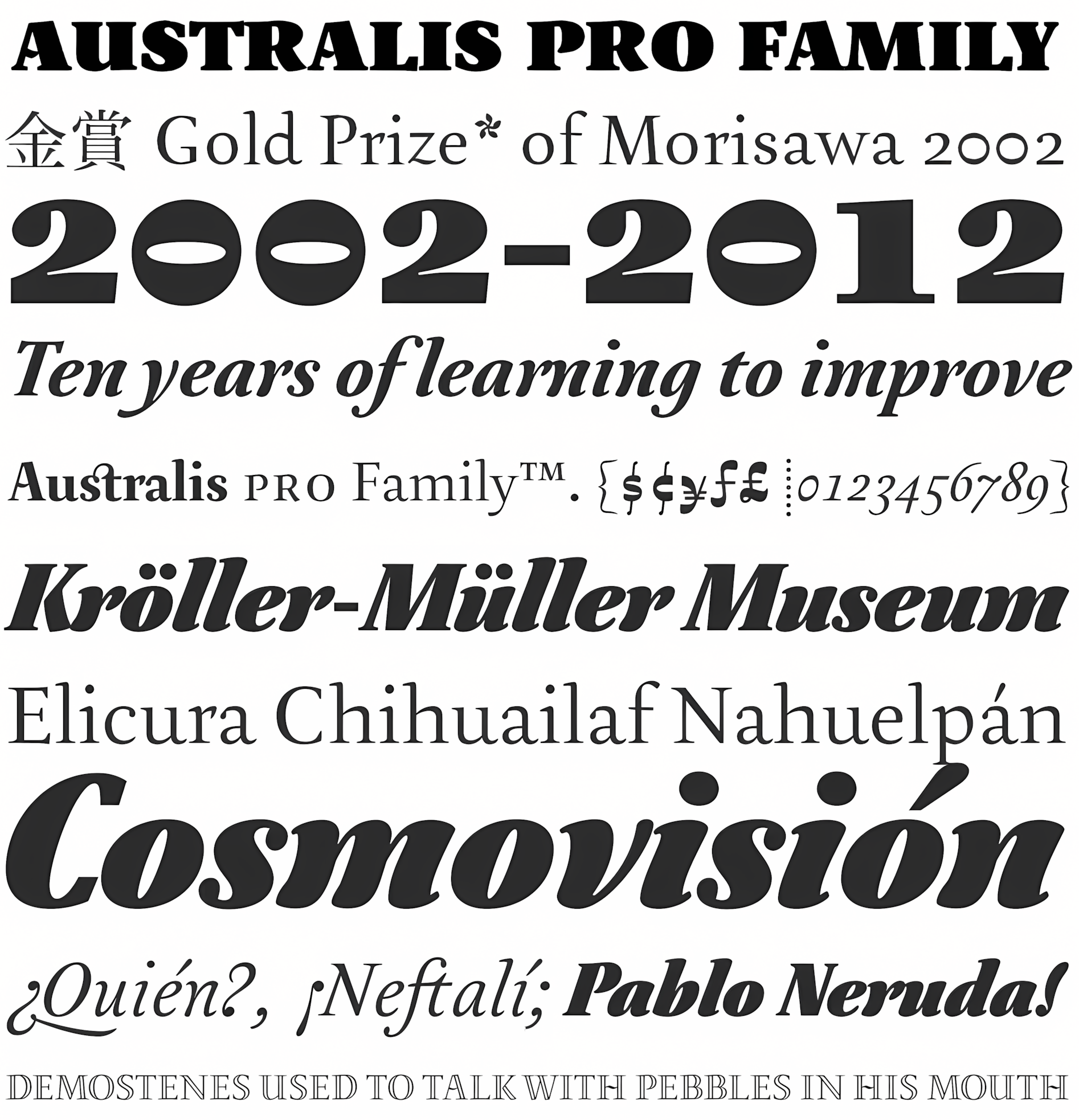
Australis Pro
| Año | 2001 — Actualizada: ( 2012 ) |
| Créditos | Francisco Gálvez |
| Descripción | Australis es una fuente romana híbrida que ganó el primer premio del Concurso Internacional de Diseño Tipográfico Morisawa en 2002. Después de 10 años, la familia está por fin completa y su lanzamiento coincide con la reapertura del concurso en 2012, en Japón. Diseñada por Francisco Gálvez Pizarro. |
| Clasificación | Texto |
| Familia(s) | Australis Pro, Australis Pro Swash |
| Estilos | 9 |
| Reconocimientos | Morisawa. Gold Prize 2002, Bienal de Tipografía Latinoamericana. Tipos Latinos 2004 |